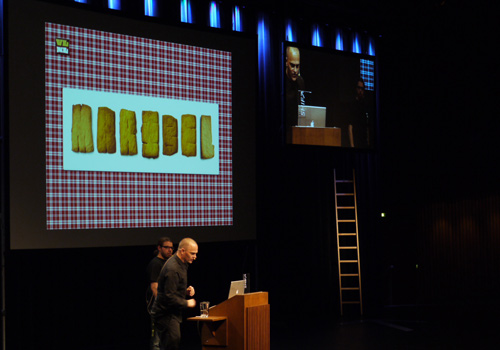
Donald und Donald von VetteLetters Foundry haben heute, wie könnte es anders sein, ein ganzes Menü zusammengestellt. Denn: We love food – and fonts. Das Menü war so groß, dass man schwer alles wiedergeben kann, aber hier kommen die Highlights.
Nachdem die beiden sich einigen konnten, wer die rechte Taste (»es ist doch die rechte Taste?!«) drückt, stellen sie ihre eigenen Schriften, Brak und SpaghettiBrokken, ein Font, der für Überraschung sorgte, als Donald seine Schrift wieder im Logo von New York City wiederentdeckte. Und die auch als Brokken Light zu erhalten ist, »für eure Gesundheit«). Erhältlich, ja »Catering machen wir auch«.
Der eine spricht, der andere trinkt und isst mal schnell was. Abwechselnd stellen sie Schriften vor, machen Werbung (»irgendwie müssen wir ja unser Geld verdienen«) und berichten von den Workshops, die sie anbieten. Die letzten Ergebnisse: mit Kartoffelstempeln Gedrucktes und Dreidimensionales aus Gemüse (»sieht super aus,– außerdem kann man es auch essen!«).
Die NeueSardines von Jacques Le Bailly ist bei Vette Letters erschienen und hat insgesamt 42 verschiedene Schnitte (»alle in einer Büchse, – um sie frisch zu halten«). Ein weiteres Highlight: Das Musikvideo That Man von Caro Emerald, für das Vette Letters die Schrift gestaltete. Während das Video läuft, essen die Donalds noch schnell zu Ende, tanzen schließlich zur Musik.
Sie erzählen von Familientreffen, Grillpartys, Cookies, russischer Schockolade, Bandlogos und vielem mehr. Gerade entsteht zum Beispiel noch die Bonbon, eine sehr schöne Schrift, von der Donald zwar nicht weiß, wo man einsetzten sollte, – »aber sie sieht gut aus«.
Seit 1984 führt Donald Beekman das Designstudio DBXL in seiner Heimatstadt Amsterdam. Er entwarf zahlreiche Logos, Platten- und CD-Cover, Flyer, Poster, CIs, Zeitschriften, Verpackungen sowie Schriften, die meist auf der Grundlage von Logos oder Artwork für seine Auftraggeber entstanden. Donald Beekman ist außerdem Musiker und seit 2004 einer der Macher des Typeradios. Seit 2008 leitet er zusammen mit Donald Roos die VetteLetters Foundry.
Donald Roos fing als Tellerwäscher an, wurde Hilfskoch, Sozusagen-Designer und schließlich Schriftgestalter bzw. CEO der leckersten Font Foundry der Welt.